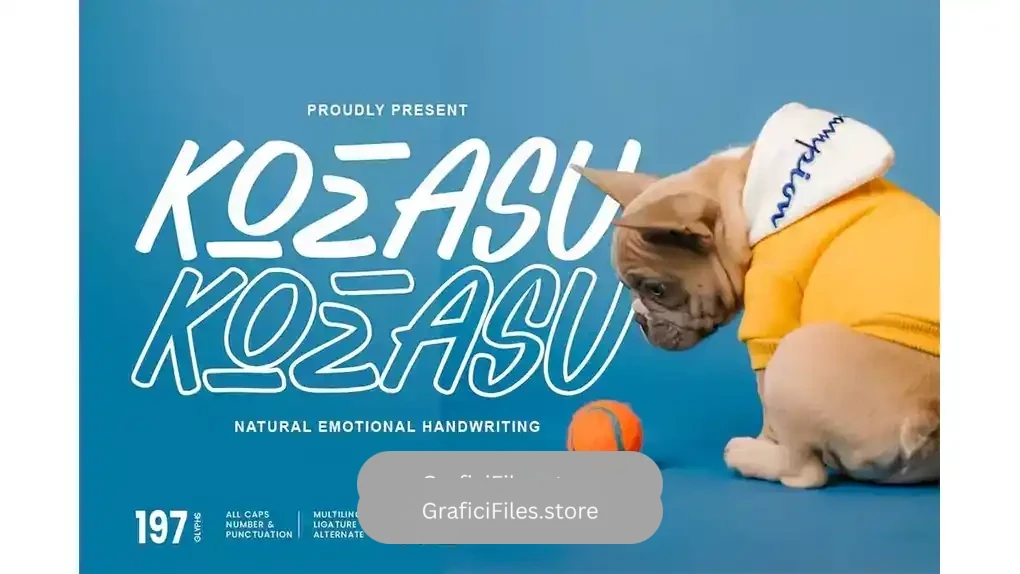
دانلود فونت انگلیسی KOEASU – Misuh Display Font
فونت انگلیسی KOEASU – Misuh Display Font : این مجموعه شامل یک فونت دست نویس است که برای لوگو، نقل قول، محصولات، تیشرت ها، بسته بندی، کمیک ها، مجلات، پوستر ها، رویداد ها، پست شبکه های اجتماعی، کتاب ها و پوشش متنی بر روی تصویر پس زمینه مناسب میباشد.
• سبک: N/A
• فضا بین حروف: معمولی
• اندازه بهینه: تمامی سایز ها